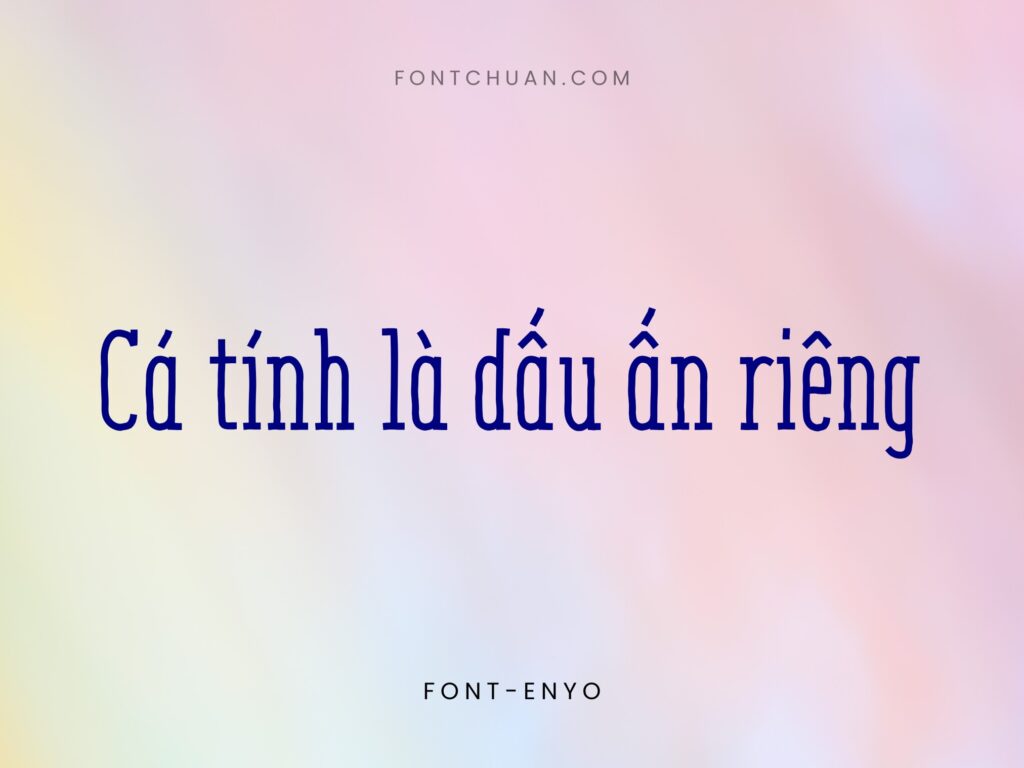
Font iCiel Enyo Việt Hóa
Enyo là một kiểu chữ serif trang trí độc đáo được thiết kế bởi Julia Martinez Diana, phát hành vào năm 2014. Font này mang phong cách viết tay với các ký tự serif, tạo nên vẻ ngoài thân thiện và không chính thức. Đặc biệt, Enyo đã được Việt hóa bởi Iciel, hỗ trợ tiếng Việt cùng nhiều ngôn ngữ khác, đáp ứng nhu cầu đa dạng của người dùng. Thành viên của Font Chuẩn đã sưu tầm và chia sẻ font này, giúp cộng đồng thiết kế ứng dụng dễ dàng trong các dự án của mình.
Về đặc điểm thiết kế, Enyo sở hữu các ký tự viết tay với nét chữ mềm mại và uyển chuyển, kết hợp với các yếu tố serif truyền thống. Font này phù hợp cho các thiết kế như tiêu đề, poster, logo, bao bì sản phẩm và các ấn phẩm quảng cáo cần sự nổi bật và cá tính. Ngoài ra, Enyo còn thích hợp cho các ngành nghề như quảng cáo, ẩm thực, thiệp cưới và spa, cùng các sự kiện đặc biệt như lễ hội, sinh nhật, Halloween và Trung thu.